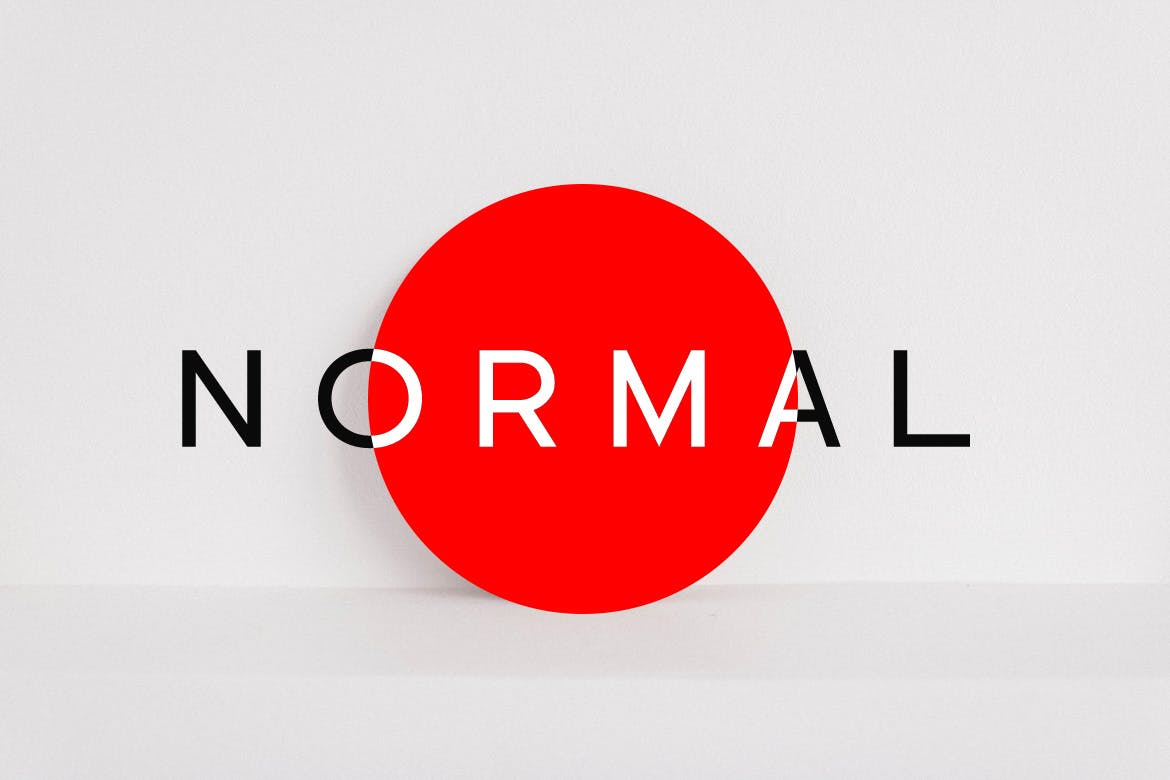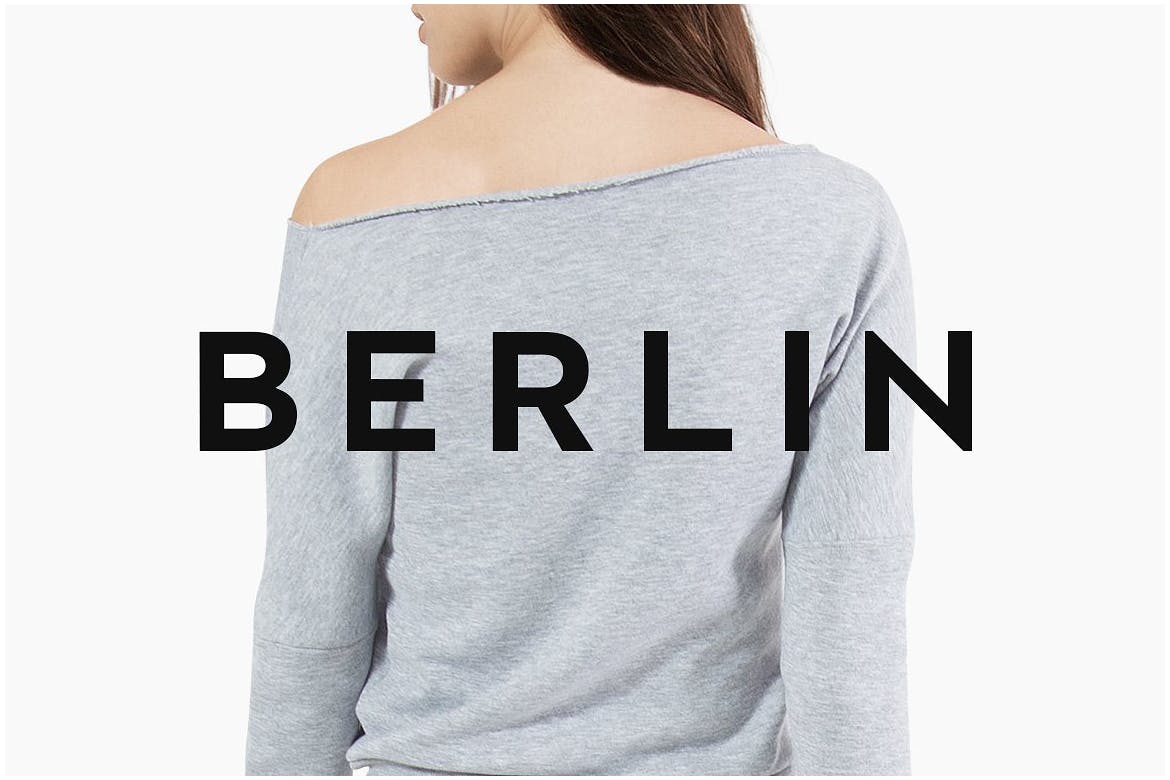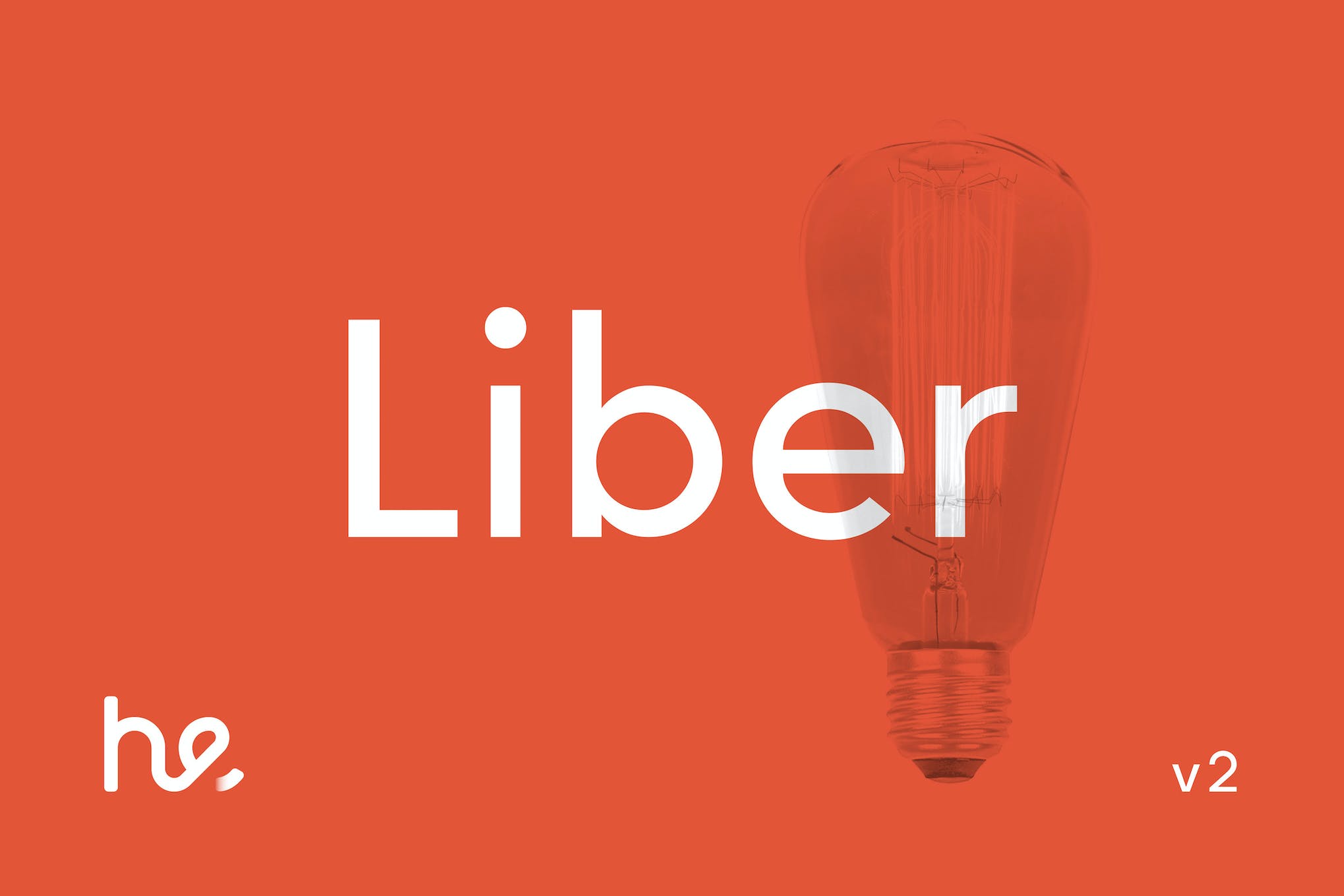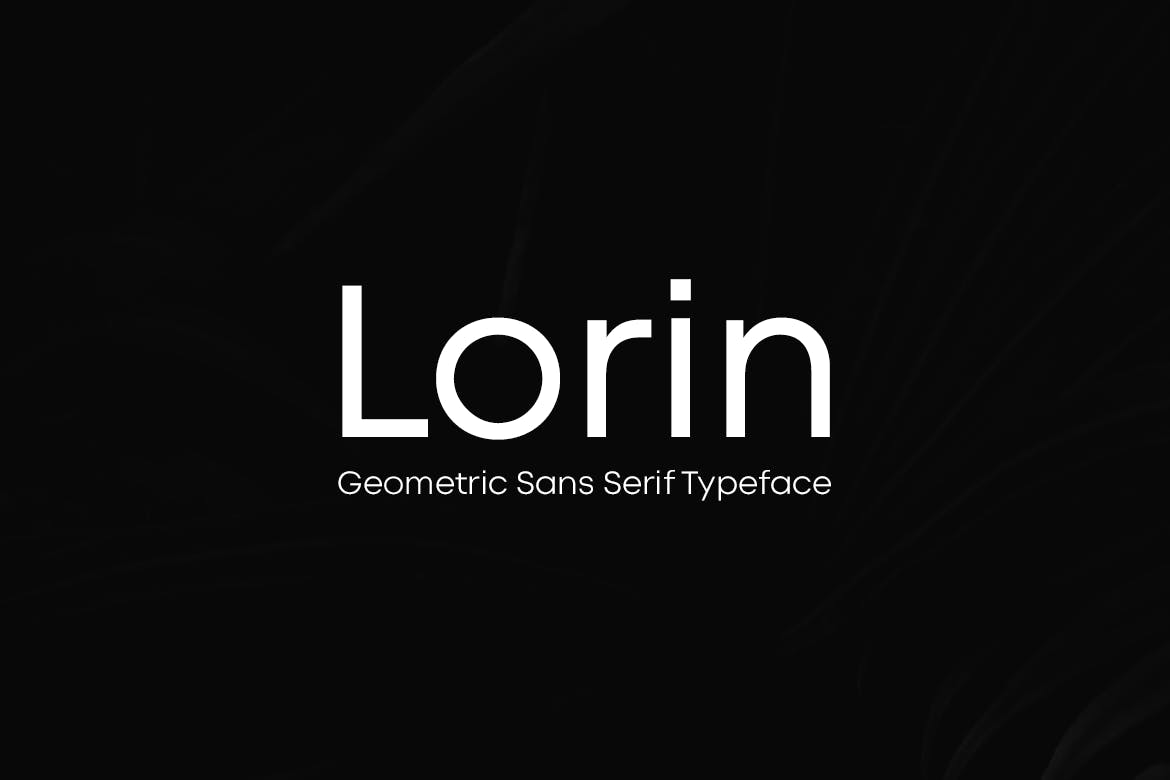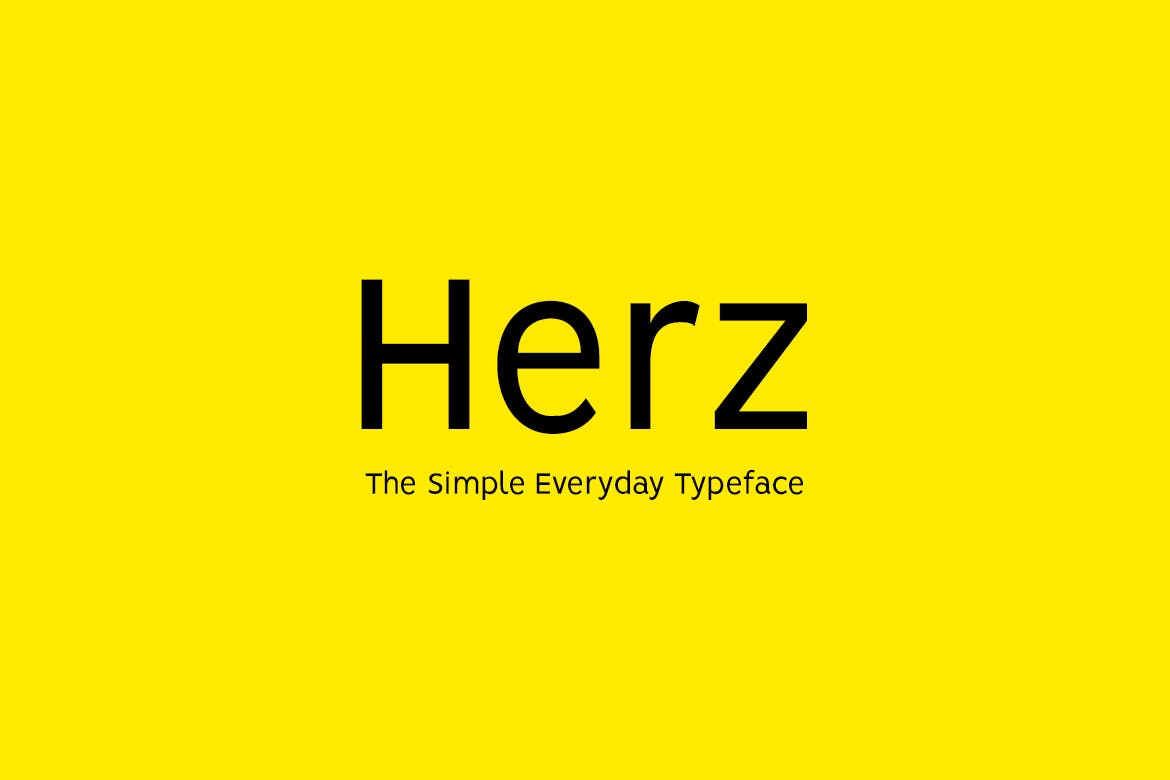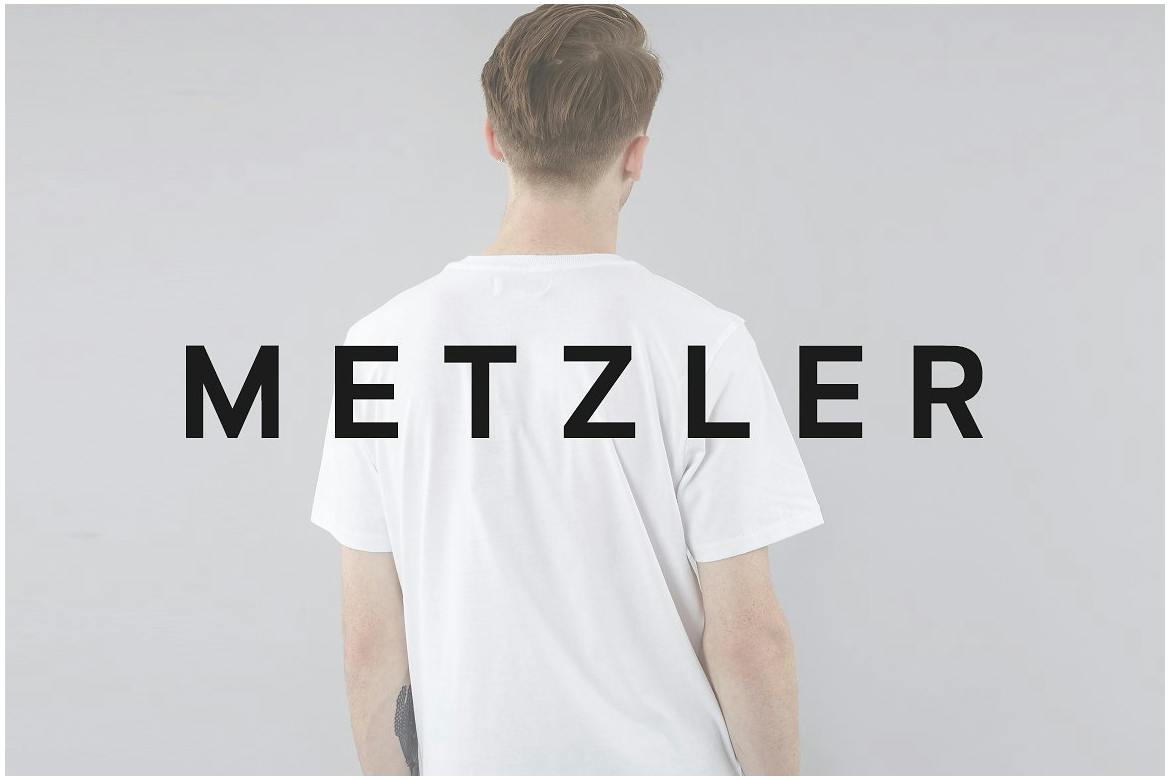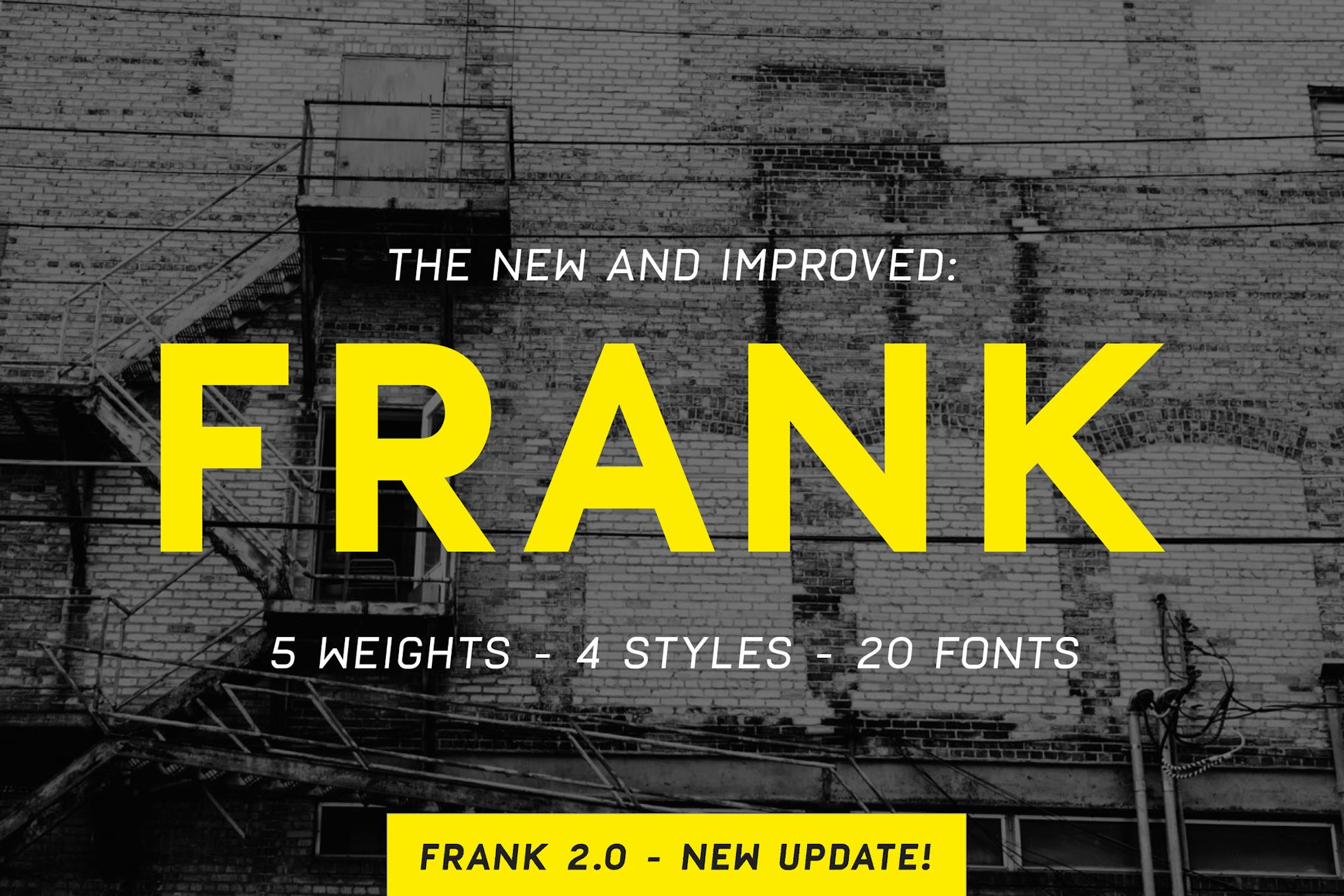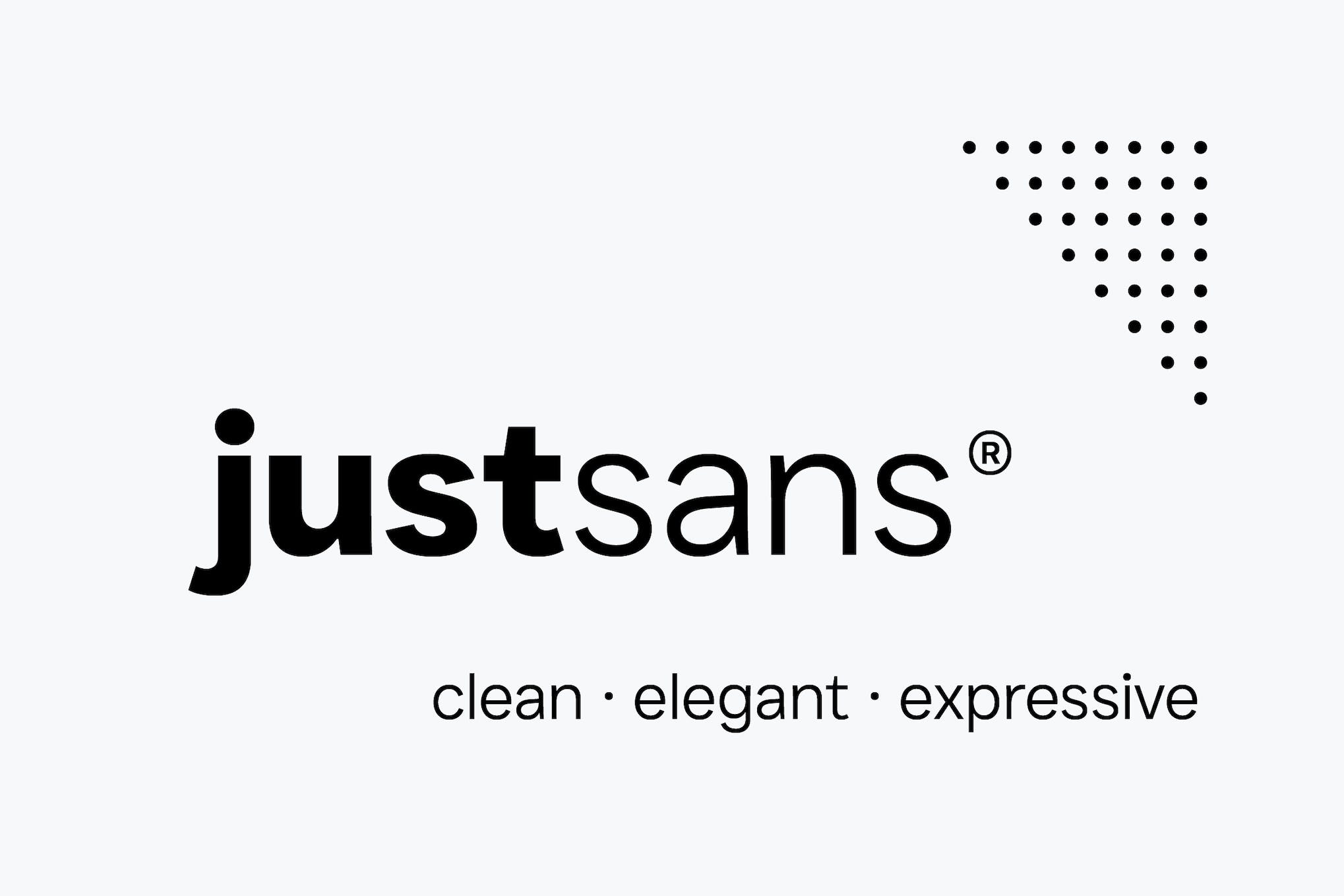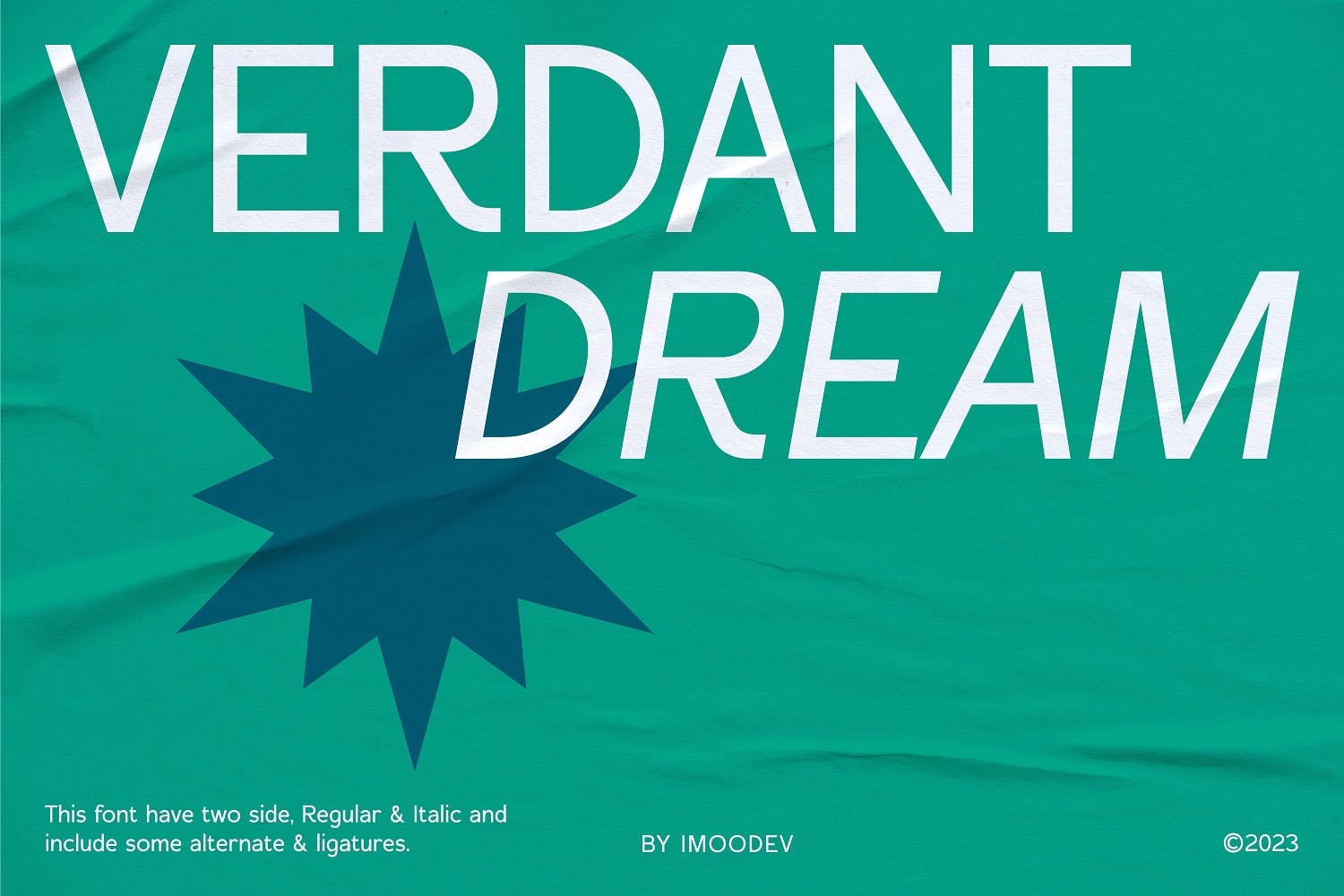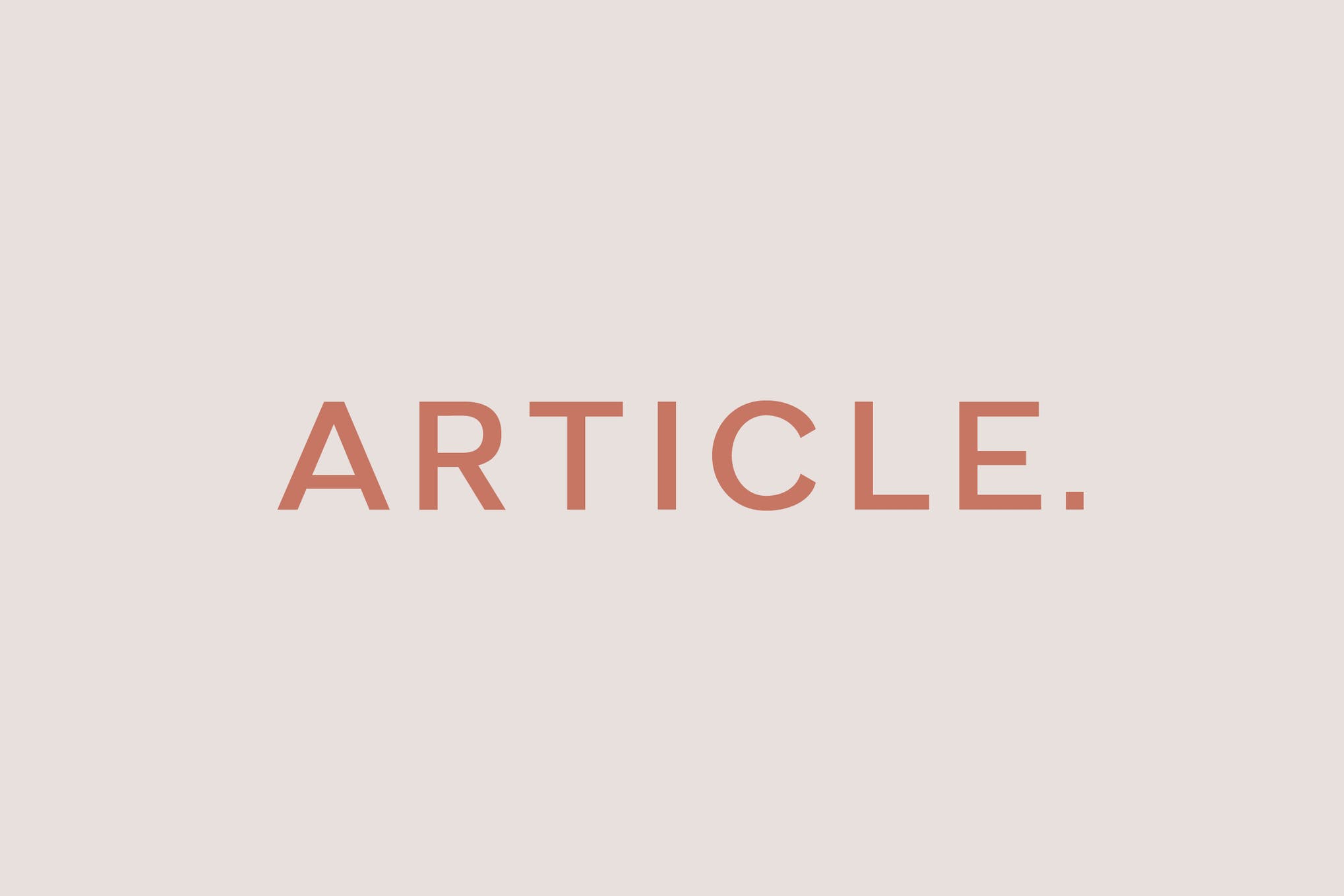
20+ Beste Fonts die der Avenir ähnlich sind
Avenir ist eine ikonische Schriftart mit einem sauberen und geometrischen Buchstaben-Design. Sie wird häufig von großen Unternehmen und Geschäften verwendet, insbesondere für Schilder- und Markendesigns. Heute erkunden wir einige der besten Schriftarten, die Avenir ähnlich sind, um Ihnen zu helfen, weitere erstaunliche Schriftarten mit dem gleichen professionellen Look zu finden, ohne die teuren Lizenzkosten.
In dieser Sammlung haben wir eine Vielzahl von handverlesenen Schriftarten zusammengestellt, die Designelemente verkörpern, die denen der renommierten Avenir-Schriftart nahekommen. Die in diesem Beitrag enthaltenen Schriftarten wurden sorgfältig ausgewählt, um Ihnen hochwertige, aber erschwinglichere Alternativen zur Avenir-Schriftart für Ihre kreativen Designprojekte zu bieten.
Besonders wenn Sie nach einem bestimmten Stil suchen, wie dem von Avenir, kann es herausfordernd sein, ähnliche Optionen zu finden, die nicht das Budget sprengen. Genau aus diesem Grund haben wir auch einige kostenlose Schriftarten in die Liste aufgenommen. Durchstöbern Sie die kuratierte Sammlung, um die perfekte Wahl für Ihr Projekt zu finden.
Liber
Liber ist eine erfrischend saubere Schriftart, die 2016 von Valerio Dell’Edera erstellt wurde. Mit einem Design, das an Avenir erinnert, kombiniert Liber die mathematische Präzision geometrischer Formen und die Lesbarkeit traditioneller Textschriften zu einer modernen, benutzerresponsiven Schriftart. Es bietet einen harmonischen Ansatz sowohl für Überschriften als auch für Inhalte und ist vielseitig einsetzbar in den Bereichen Branding, Redaktion und Beschilderung.
HERZ
HERZ, eine stilvolle Sans-Serif-Schriftart mit einem modernen Touch, eignet sich perfekt für verschiedene Anwendungen, von Logos bis hin zu Überschriften und Branding. Diese unverwechselbare Schriftart bietet drei Gewichtungen – light, regular und bold. Darüber hinaus ist sie mit OTF, TTF und einer Vielzahl von Webfont-Stilen ausgestattet. Sie hat auch den sauberen Look der Avenir-Schriftart.
NORMAL
NORMAL ist eine vielseitige Schriftart mit einem Design ähnlich wie Avenir. Ihr reines, minimalistisches Design verleiht ihr einen einzigartigen Charme und Vielseitigkeit, was sie zu einer guten Wahl für Logos, Überschriften, Branding sowie für Web- und Druckzwecke macht. Mit fünf verschiedenen Gewichtungen von ExtraLight bis ExtraBold und Verfügbarkeit in den Formaten OTF, TTF und Web Fonts ist sie eine vielseitige Ressource für jedes kreative Projekt.
BERLIN
BERLIN ist eine moderne, minimalistische Schriftart, die von klassischen geometrischen Schriftarten inspiriert ist und perfekt für stilvolle Überschriften in Mode-Webshops oder minimalistischen Portfolios geeignet ist. Die Schriftart kommt mit vier Gewichtungen und mehreren Formaten für ultimative Vielseitigkeit. Sie ist auch eine großartige Alternative zur Avenir-Schriftart.
LORIN
LORIN ist eine stilvolle, moderne geometrische Sans-Serif-Schriftart mit Fokus auf Ästhetik. Inspiriert von klassischen geometrischen Schriftarten wie Avenir bietet LORIN eine einzigartige Note für verschiedene Inhalte von Logos bis zu großen Postern. Verfügbar in vier Gewichtungen (light, regular,
bold, extra bold) wird sie mit Buchstabenspatiierung noch unverwechselbarer.
METZLER
Die METZLER-Schriftart mit modernem Sans-Serif-Stil spiegelt klassische geometrische Schriftarten wider, bietet jedoch eine frische Wendung. Ideal für alles von Kurztext bis zu modischen Überschriften, verleiht diese Schriftart eine anspruchsvolle Note und ist perfekt für Luxusproduktetiketten oder hochwertige Websites. Mit drei Gewichtungen (Light, Regular, Bold) und den entsprechenden kursiven Versionen ist das Paket eine vielseitige Wahl für jedes kreative Projekt.
Frank
Werfen Sie einen Blick auf Frank, eine faszinierende Schriftart, die von klassischen Schriften wie Avenir und Futura inspiriert ist. Perfekt zugeschnitten für den Einsatz in Drucken, T-Shirts und Postern, bietet sie fünf Gewichtungen und kommt in drei einzigartigen Stilen: normal, oblique und rough. Sie hat auch über 300 Glyphen.
Orion Pro
Orion Pro ist eine vielseitige Schriftfamilie, die populären Schweizer Schriftarten huldigt. Ihr moderner Sans-Serif-Stil macht sie zu einer exzellenten Wahl für verschiedene Anwendungen, wie Überschriften, Branding und Marketinggrafiken. Sie umfasst 12 einzigartige Schriftarten, mit jeweils sechs Gewichtungen in regulären und kursiven Versionen.
VISIA Pro
VISIA Pro ist eine geometrische Sans-Serif-Schriftart, die Eleganz und Minimalismus geschickt für ein Premium-Design kombiniert. Als vielseitige Schriftart eignet sie sich perfekt für Logos, Überschriften, Branding und alle Arten von Web- oder Druckzwecken. Sie bietet sieben einzigartige Gewichtungen, einschließlich einer kursiven Version für jedes Gewicht.